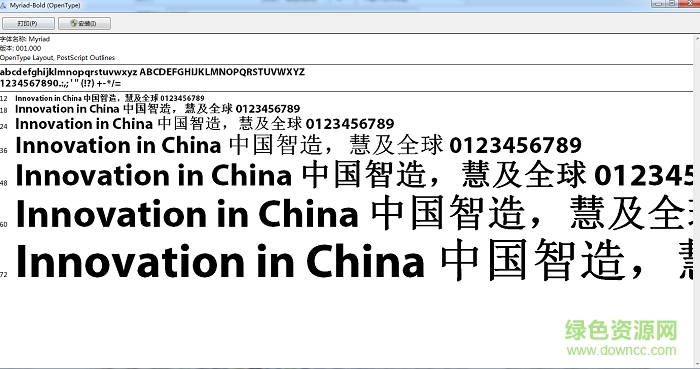
myriad bold字體是一款看著非常舒服的英文字體,字體的比例間隔完美,纖細又飽滿,識別性強,屬于無襯線字體,適合各個領(lǐng)域,感興趣的朋友快來下載吧!
無襯線體往往被用在標題、較短的文字段落或者一些通俗讀物中。相比嚴肅正經(jīng)的襯線體,無襯線體給人一種休閑輕松的感覺。隨著現(xiàn)代生活和流行趨勢的變化,如今的人們越來越喜歡用無襯線體,因為他們看上去“更干凈”。